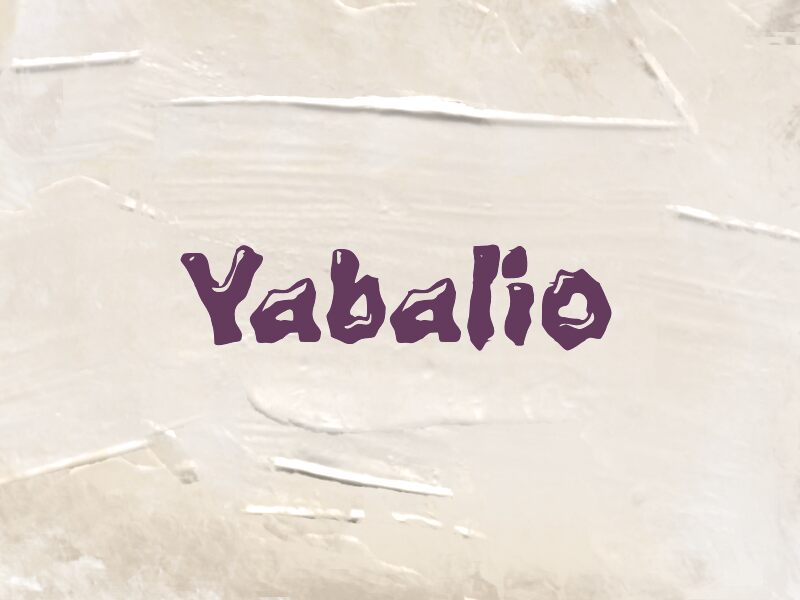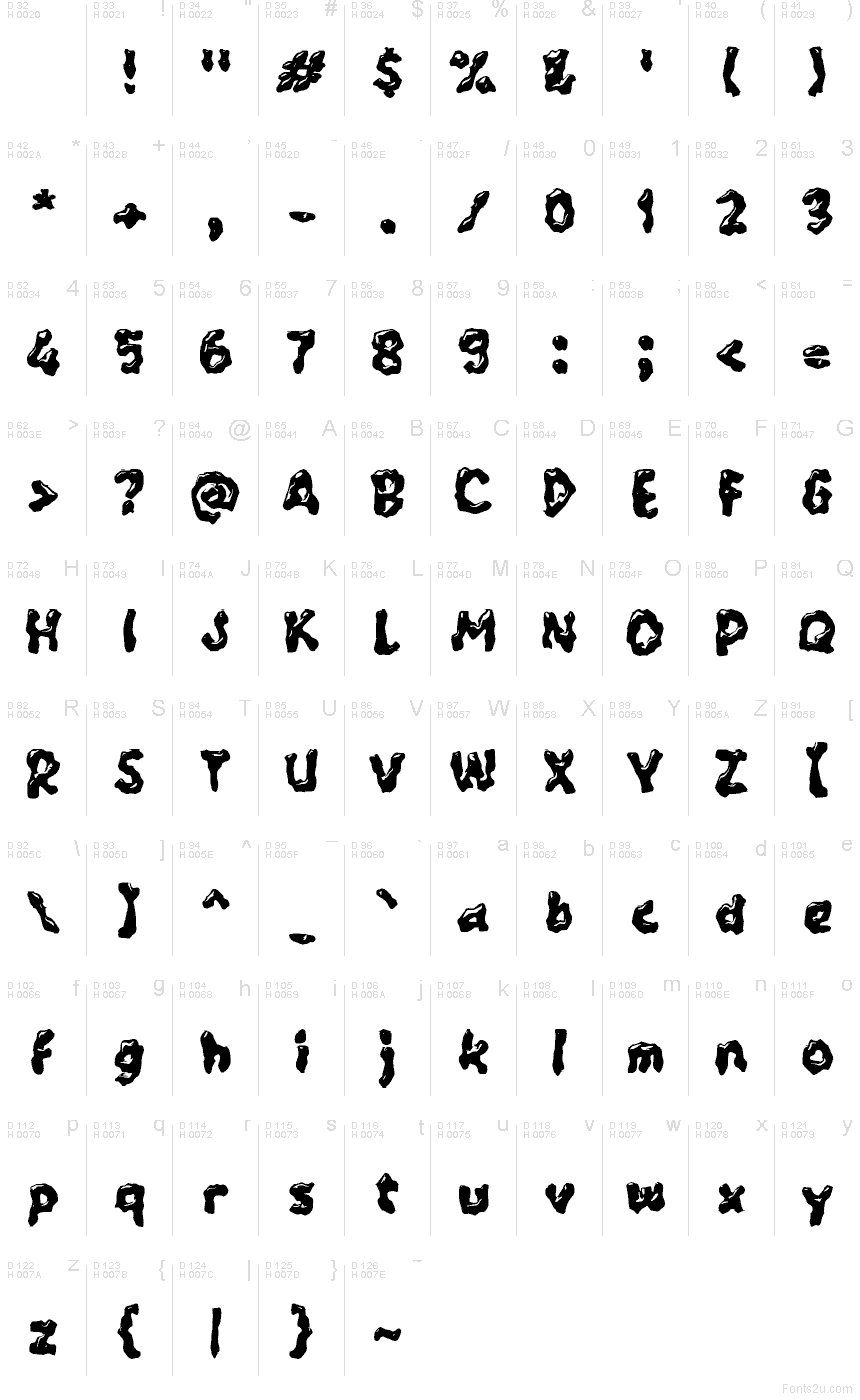
Yabalio
Yabalio, criada pela Wep, é uma fonte display gratuita estilo cartoon, moldada por silhuetas irregulares e marcantes que parecem esculpidas, achatadas e propositalmente desalinhadas. As bordas irregulares e os pequenos recortes brancos dão às letras um ar travesso e artesanal, fugindo do óbvio das fontes arredondadas ou estilo bolha.
Essa estética de quadrinhos ganha vida em capas de livros infantis, flyers de festas, logotipos lúdicos, embalagens de snacks e miniaturas de YouTube, onde as letras precisam de um toque animado e irreverente. Funciona melhor em títulos curtos e branding, especialmente quando você deseja um ritmo instável e recortado em vez de um estilo de cabeçalho polido.